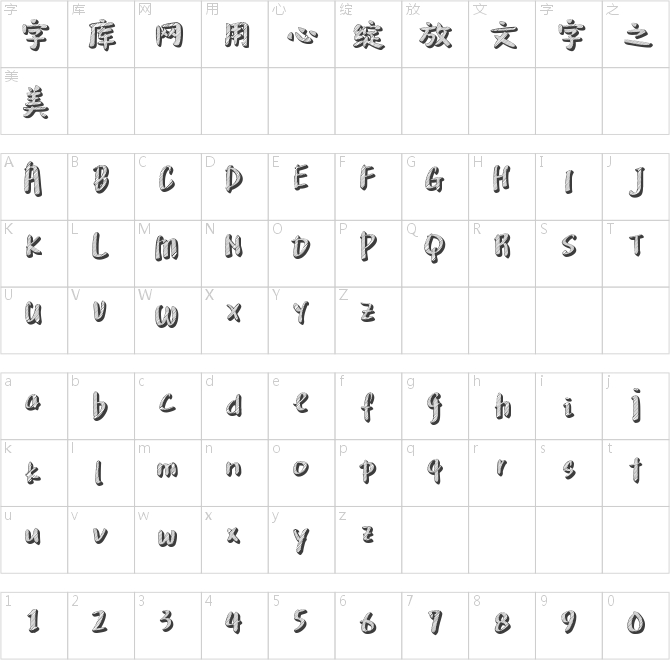
漢儀新蒂棉花糖黑板報(bào)B字體下載HanyiSentyMarshmallowChalk-B
漢儀新蒂棉花糖黑板報(bào)B字體HanyiSentyMarshmallowChalk-B字庫(kù)是一款讓人賞心悅目、百看不厭的中文字體,適合各類廣告和產(chǎn)品包裝設(shè)計(jì)應(yīng)用,字體大小32.29MB,格式為ttf字體,上傳用戶是373790005,作者/版權(quán)方為漢儀字庫(kù)